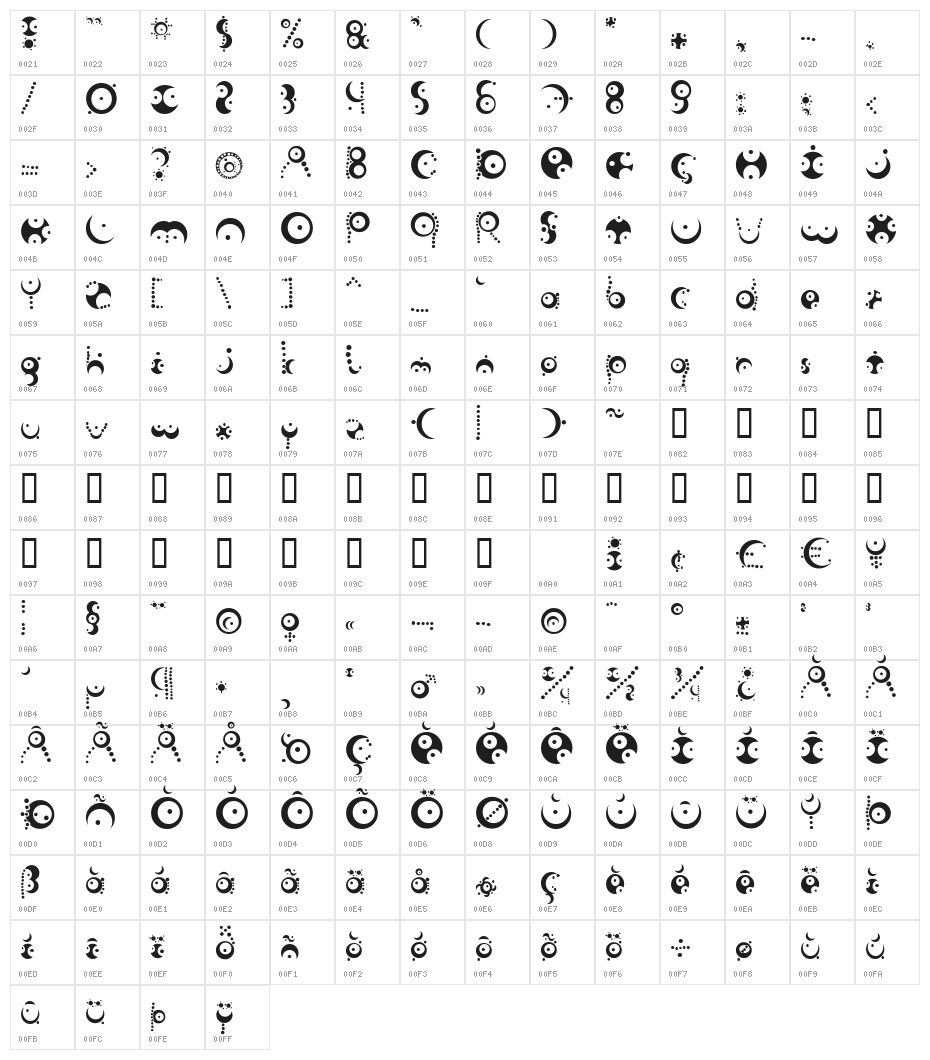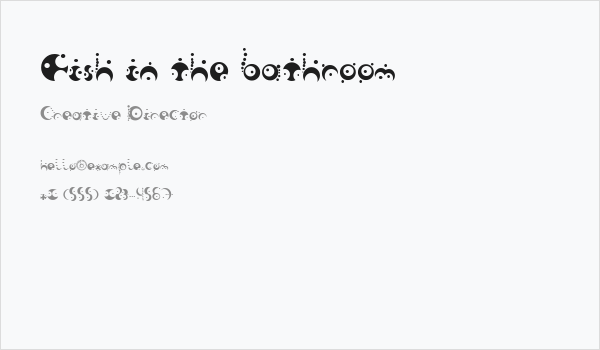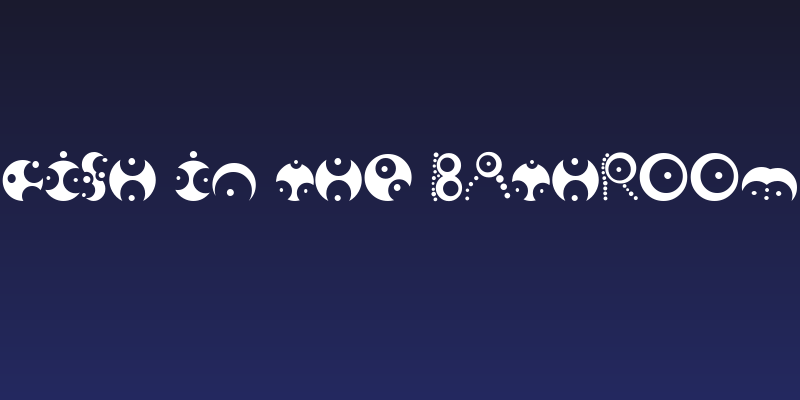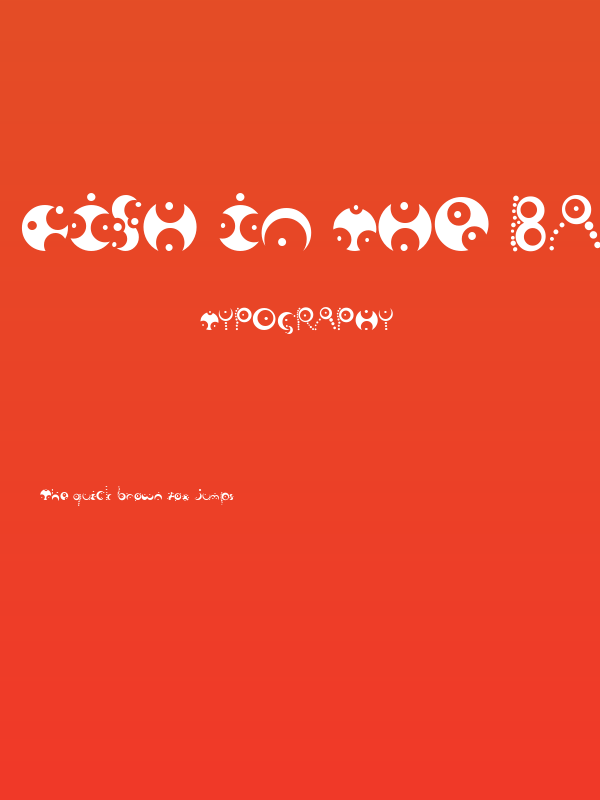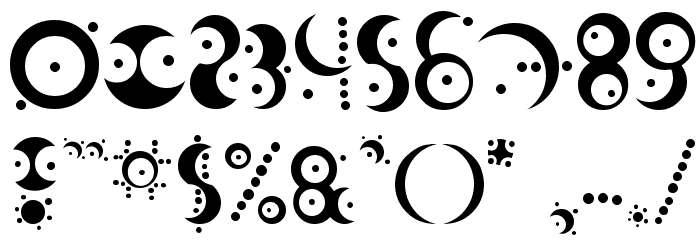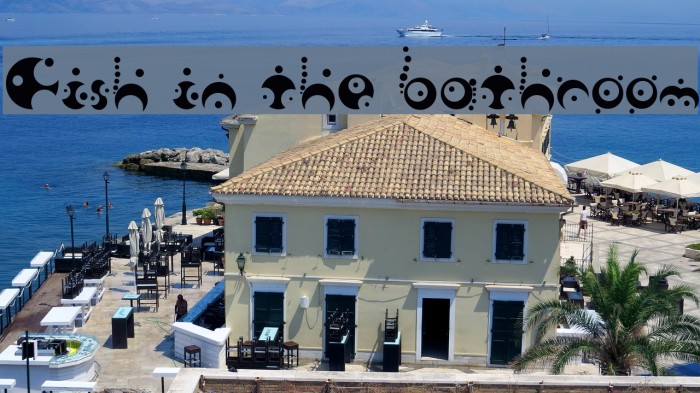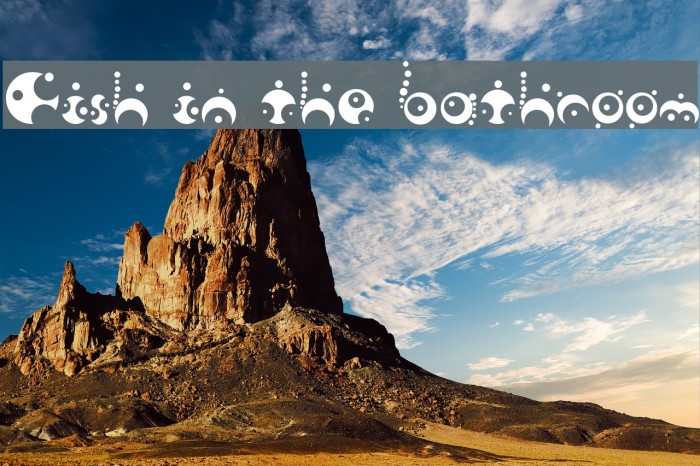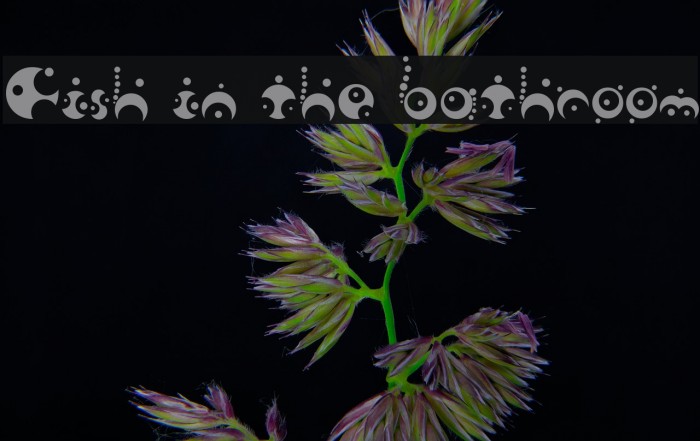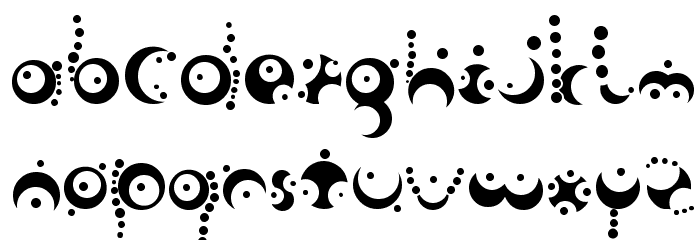
Fish in the bathroom Font
✎ bubble letter
| Style général | Modern, Decorative |
| Cas d'utilisation | Logos, Headlines, Artistic projects |
| Projets proposés | Ideal for artistic projects, creative branding, children's books, and playful graphic designs. |